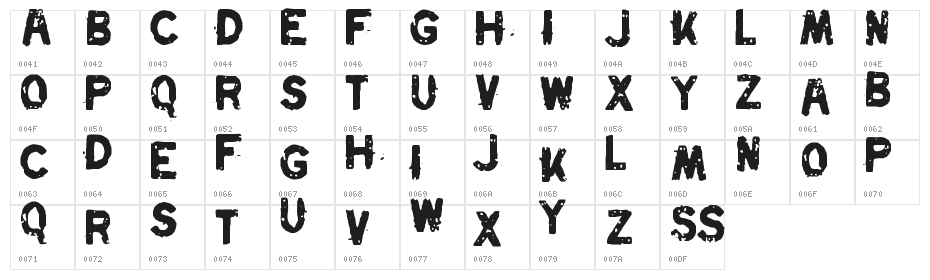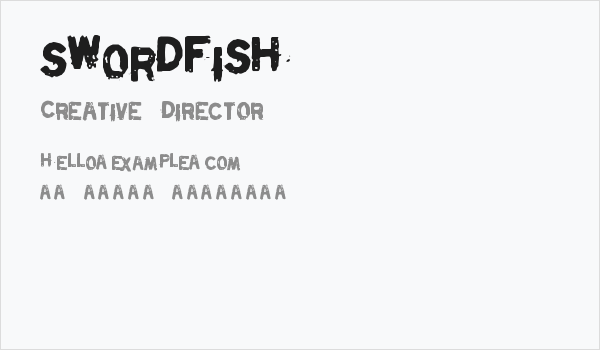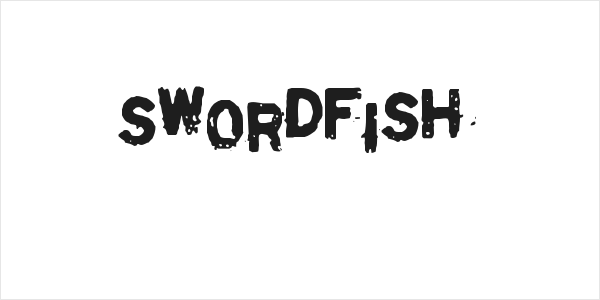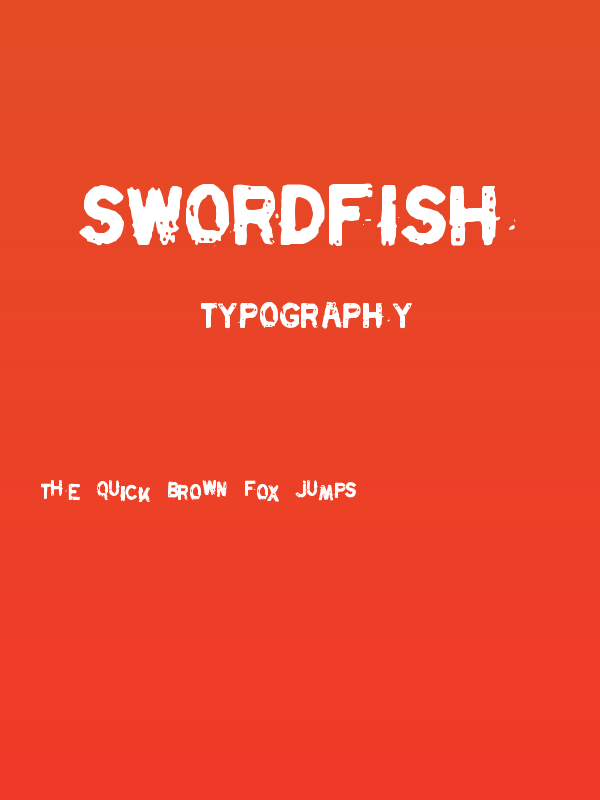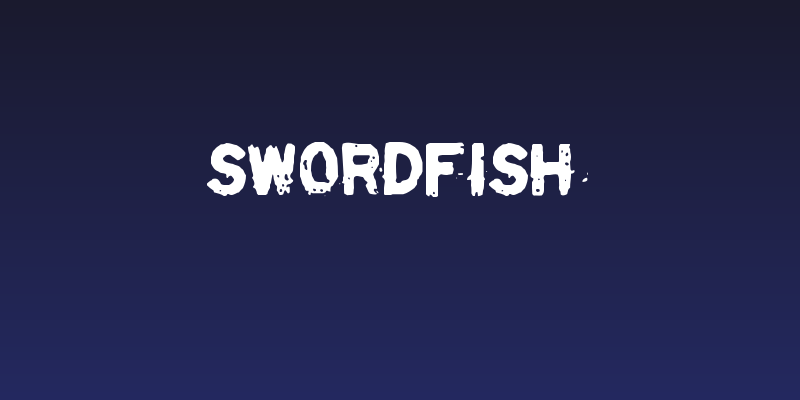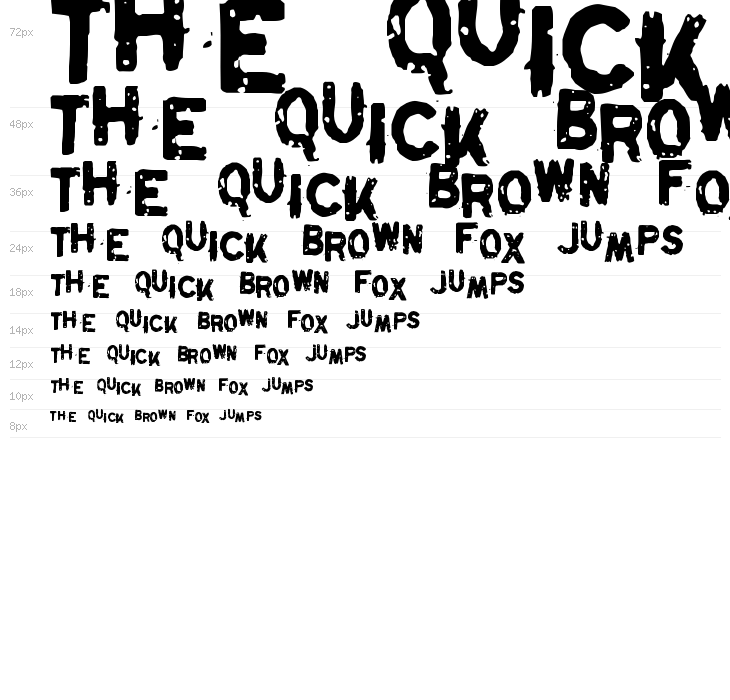
Swordfish Font
✎ Messy
| النمط العام | Grunge, Edgy, Bold |
| مشاريع مقترحة | Ideal for album covers, posters, branding for edgy or alternative products, and any design needing a bold, textured statement. |